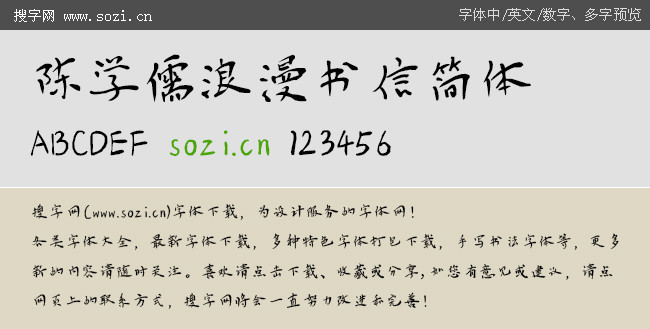
陳學(xué)儒浪漫書信簡體
搜字網(wǎng)提供一款陳學(xué)儒浪漫書信簡體中文字體下載,陳學(xué)儒浪漫書信簡體是一款手寫風(fēng)格的書法字體。字體字形飄逸,筆鋒細(xì)膩,充滿浪漫氣息,適合應(yīng)用于海報(bào)設(shè)計(jì)、書籍裝幀、畫冊(cè)封面、產(chǎn)品包裝設(shè)計(jì)等應(yīng)用。